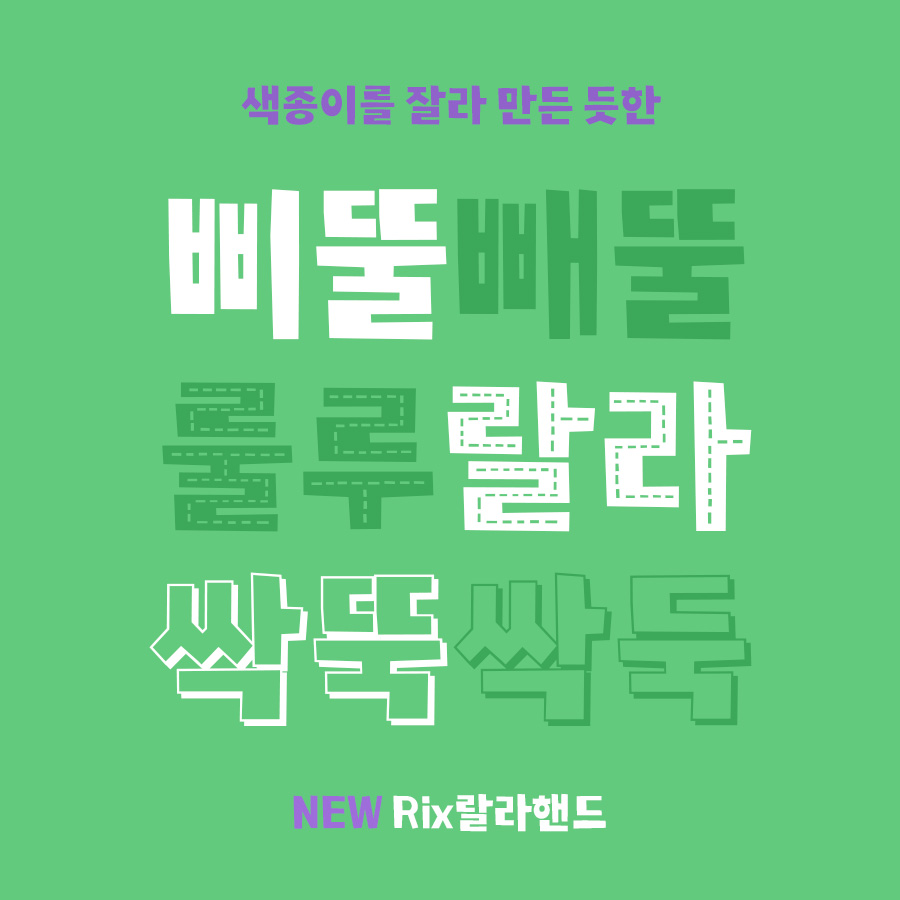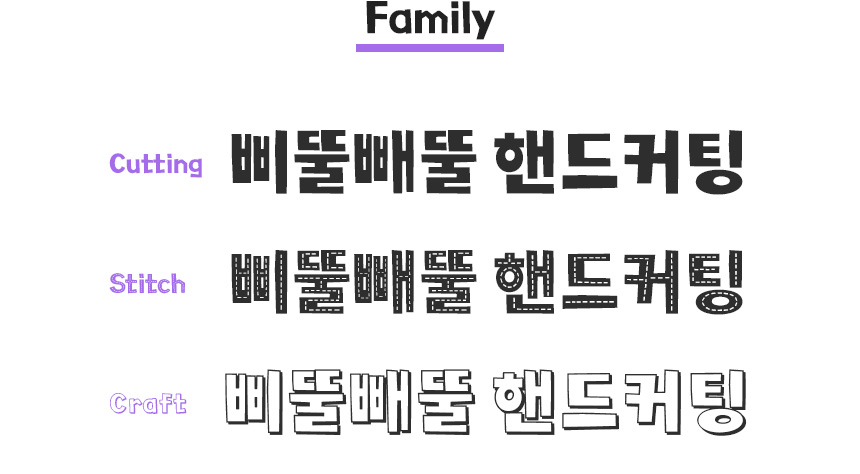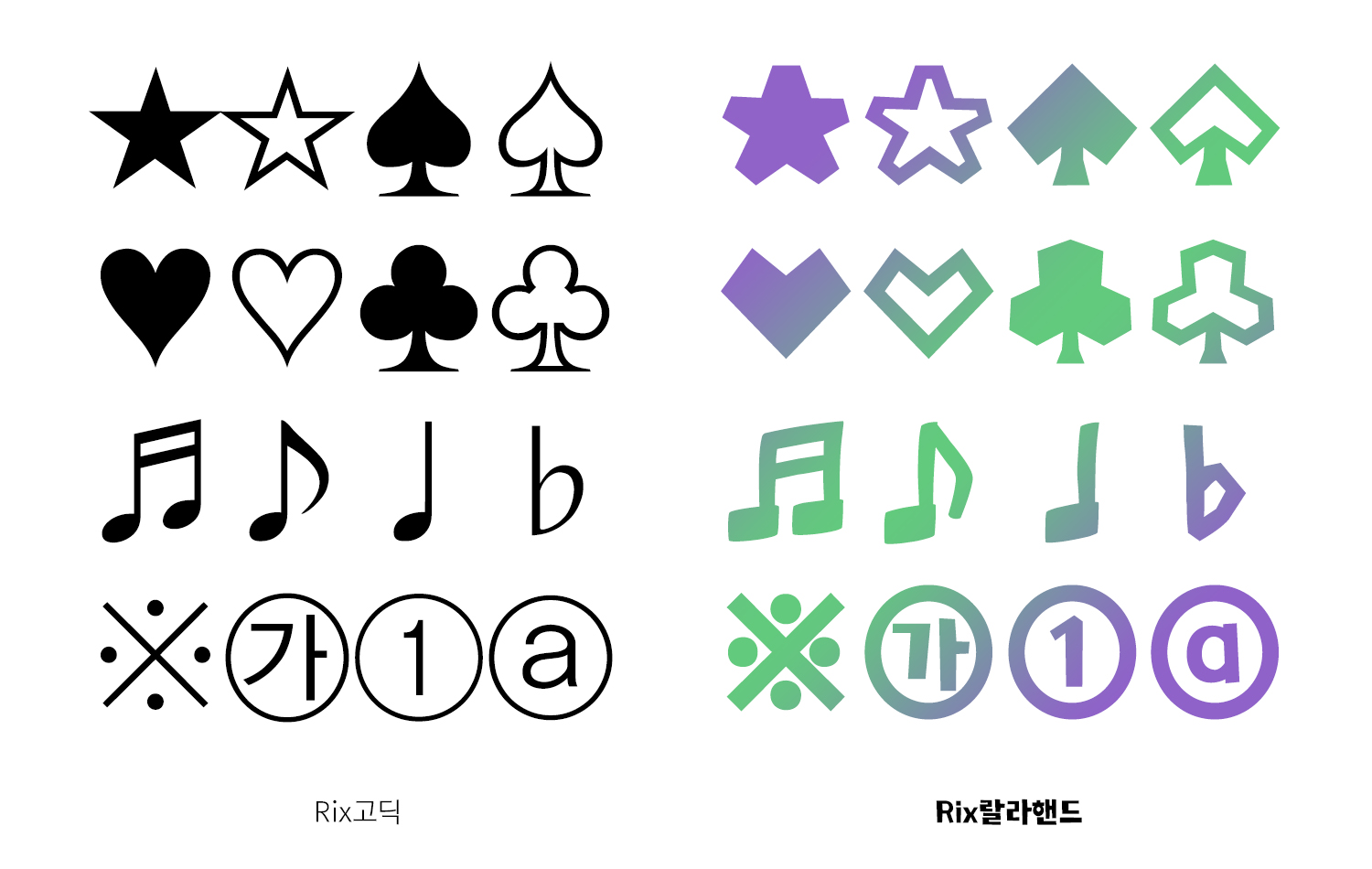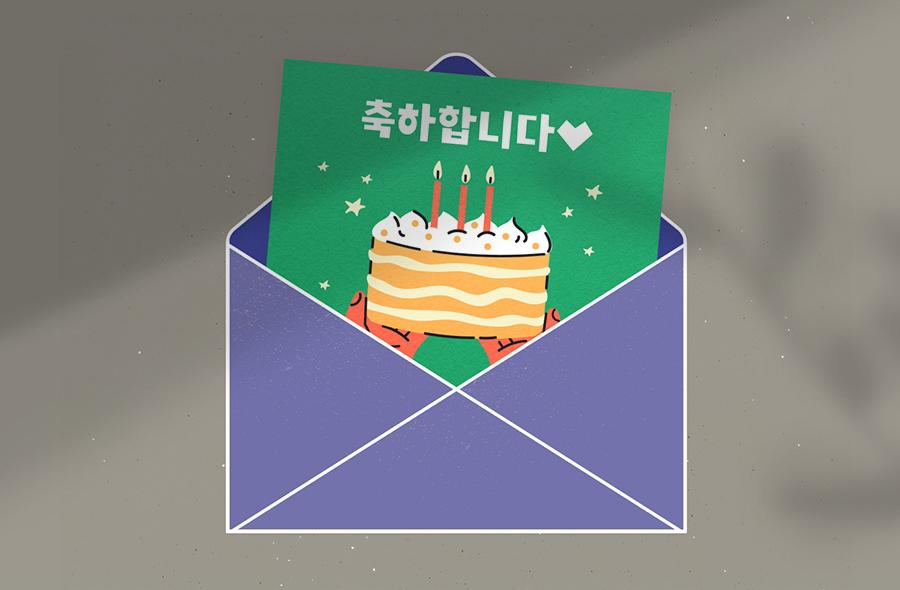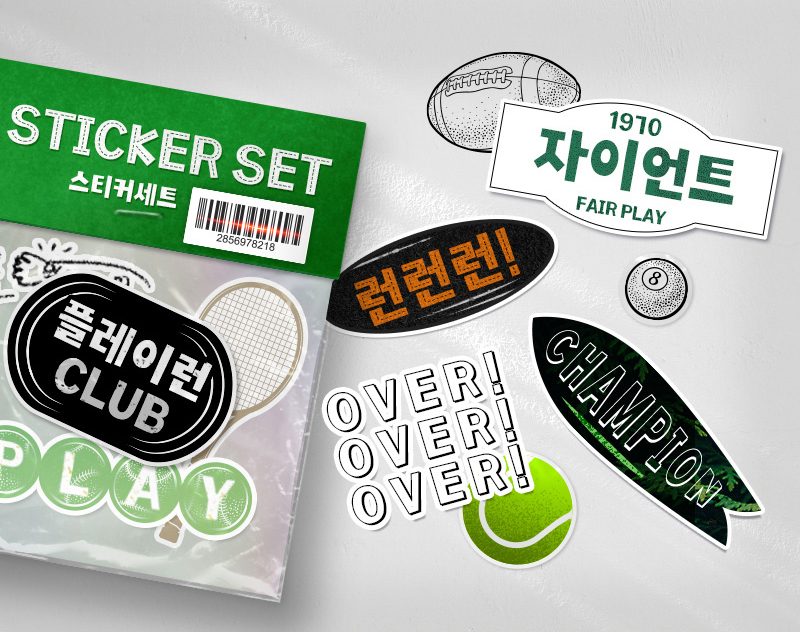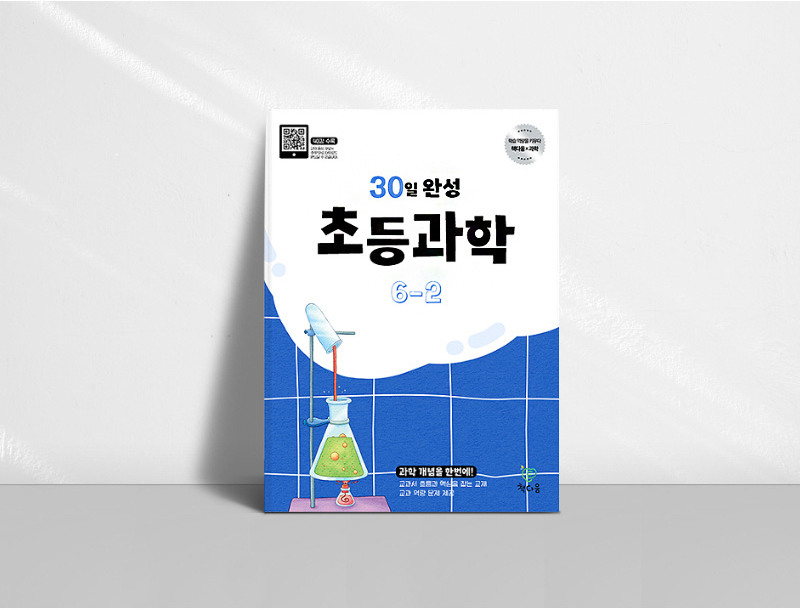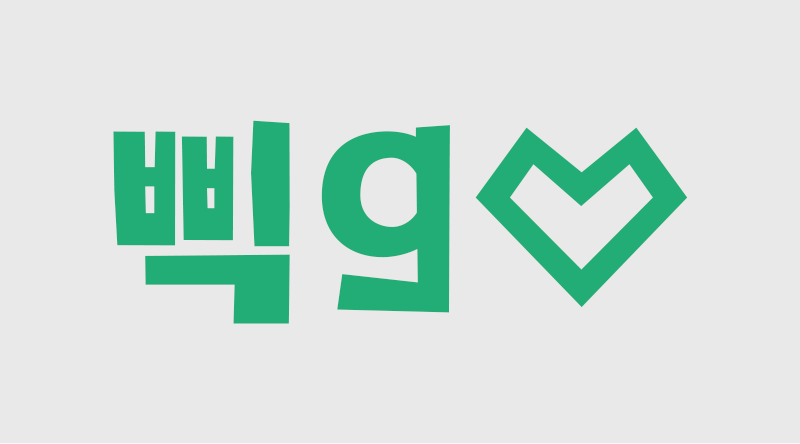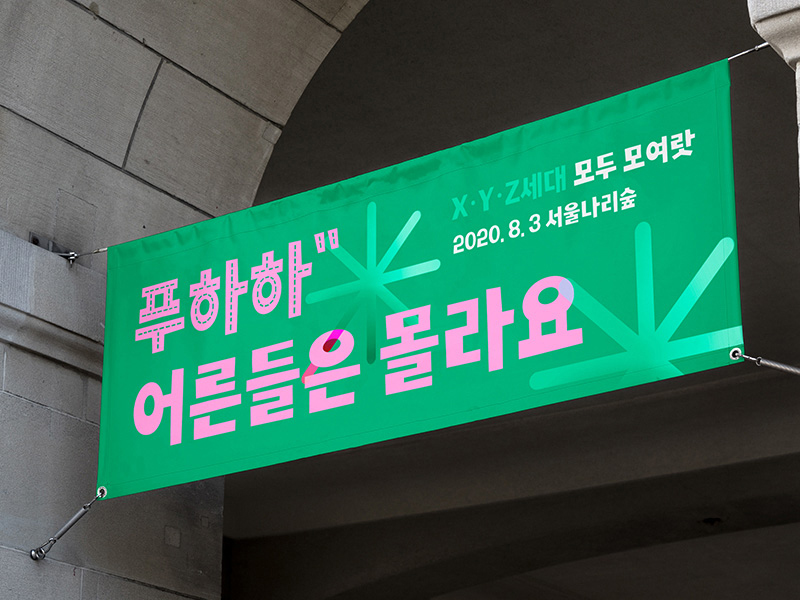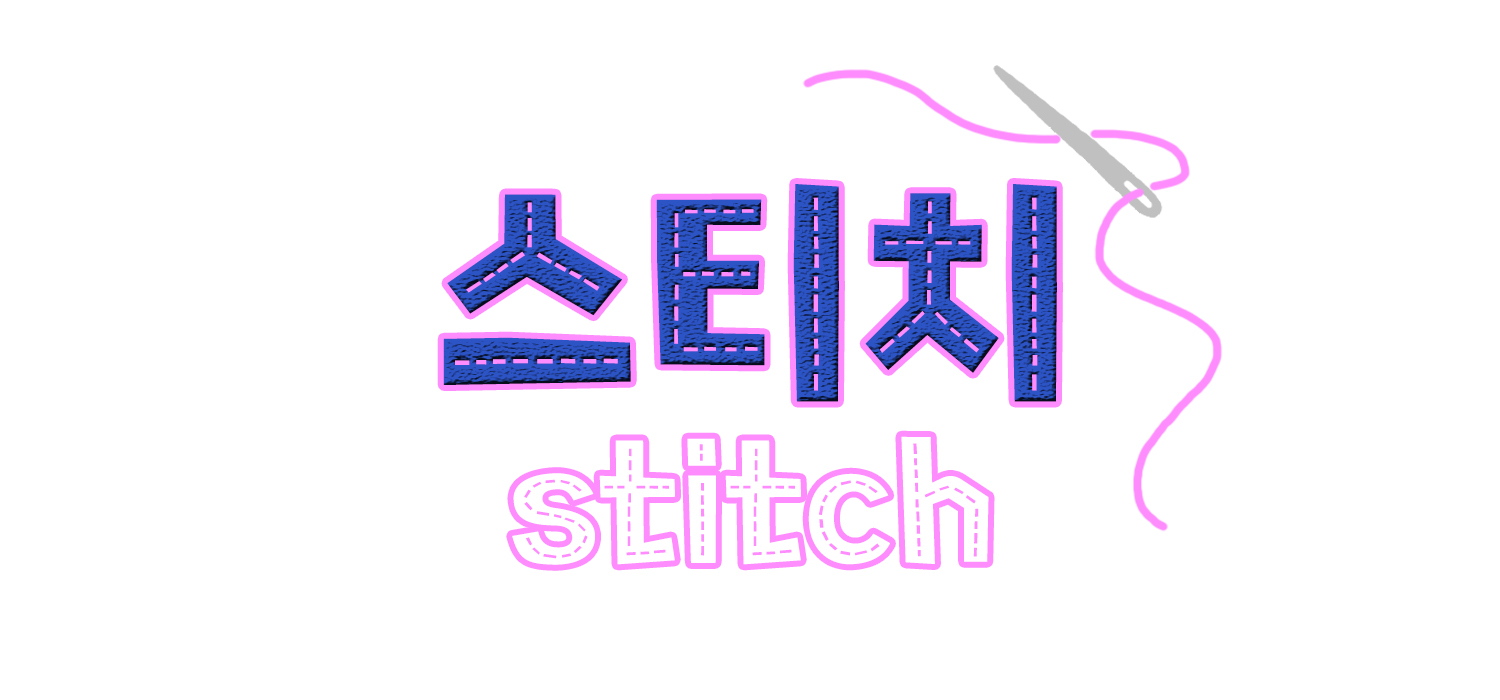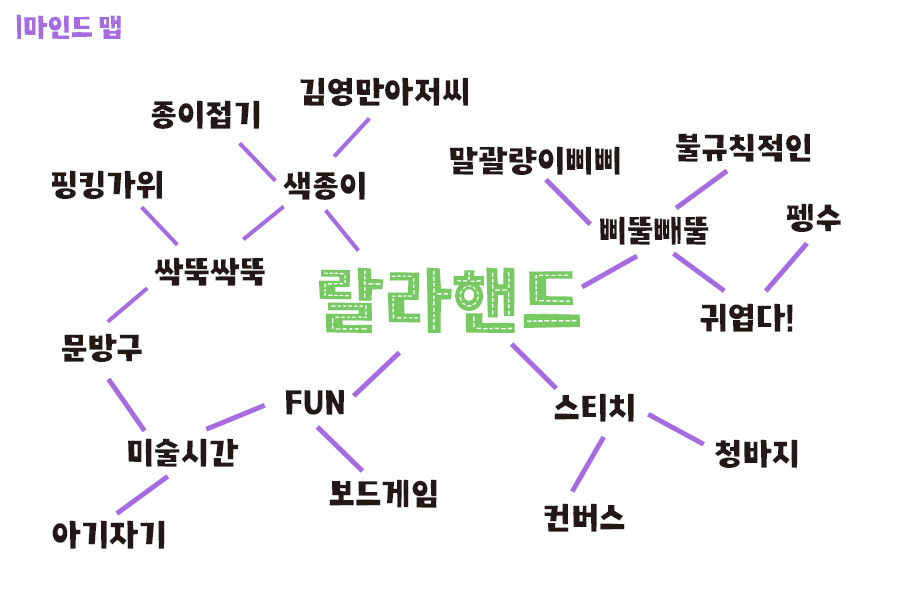
색종이를 잘라 삐뚤빼뚤, Rix랄라핸드
릭스폰트의 8월 신서체를 소개합니다. 보자마자 사랑스러워버리는 「Rix랄라핸드」라는 이름을 갖게 된 친구예요.(이름마저 귀여운 너란 폰트ㅠ) 색종이를 삐뚤빼뚤 잘라 만든 자유분방함 그 자체. 자세히 보면 볼수록 매력에 빠져드는 폰트! 먼저 폰트를 디자인해주신 김수정 디자이너와 인터뷰한 내용 함께 보실까요?
폰트를 알려면 디자이너를 알아야지_폰트 디자이너 인터뷰
폰트를 딱 보자마자 '귀엽다!'라는 생각을 했는데요. 어떻게 기획하게 되신 서체인가요?
회사에서 매달 아이디어 회의를 진행하고 있었는데, 회사에 필요한 서체가 무엇일까 고민을 하였고 다양한 자료를 조사하였습니다. 그러던 중 '핸드컷팅'이라는 소재를 글자에 적용하면 재미있겠다 생각이 들어 제작하게 되었습니다.
제작자피셜! 'Rix랄라핸드' 폰트의 가장 매력적인 부분은?
'Rix랄라핸드'는 Cutting, Stitch, Craft 3종으로 이루어진 폰트입니다. Cutting을 기본형으로, 다이어리 꾸밀 때 한 번쯤 해 보았던 드로잉(낙서) 참고하여 Stitch, Craft 효과를 만들었습니다. 형태적으로 삐뚤빼뚤, 자소 비대칭 형태가 매력적이라고 생각합니다. 효과가 들어간 Stitch, Craft 같은 경우에는 18pt이상으로 사용했을 때 디테일이 살아 더 예쁘게 사용 가능합니다. 효과와 효과를 오버랩하여 그래픽적으로 다양하게 사용할 수 있는 점이 매력포인트 같습니다.
본격 Rix랄라핸드 파헤치기.
폰트가 탄생하기까지는 7월 신서체 소개 포스팅에서도 언급했듯 정말 많은 시간과 과정들이 필요합니다. 「Rix랄라핸드」역시 수 개월의 디자인 작업 후에 여러 아이디어와 생각들이 모여 이름이 완성되고, 출시하는 단계까지 오게 되었는데요! 까도 까도 계속 나오는 양파 같은 매력의 이 폰트, 중요한 부분 중 하나인 폰트명이 만들어진 과정부터 함께 보시겠습니다*´∀`*
「랄라 핸드」라는 폰트명이 다소 생소할 수 있는데요, 이 이름은 신나고 기쁠 때 노래하는 표현인 '룰루랄라'의 랄라와 손으로 잘라서 만든 것을 뜻하는 '핸드컷팅(Hand Cutting)'의 핸드를 합쳐 만든 말입니다. 마인드 맵에서 보이듯 다양하고 재미있는 표현과 단어들이 떠올랐던 아이에요.
팀원들 대부분 이 글씨를 봤을 때 뭔가 자유분방하고 즐거운 느낌을 받았고, 아이들이 색종이를 잘라 만든 듯한 형태로 느껴져 폰트명으로 '랄라핸드'가 최종 선정되었답니다. 글씨를 써 보면 더 확실히 느낄 수 있을 거예요. 기대하시라!
매력 포인트 하나. 특수문자도 랄라핸드화
어떤 부분이 다른지 확실히 비교해드리고자 베이직한 본문형 서체로 잘 알려진 'Rix고딕'과 비교해 보았는데요. 가위로 잘라 만든 글씨처럼 특수문자에도 적용된 랄라핸드 스타일. 특히 음표들 표현된 게 참 귀엽고 사랑스럽더라고요ღ'ᴗ'ღ
*Cutting/ Stitch/ Craft 3가지 패밀리 중 어느 것을 적용해도 특수문자는 아래와 같이 국문과 동일한 스타일로 적용됩니다.
매력 포인트 둘. 개성 넘치는 패밀리
위에 잠깐 언급했던 대로 「Rix랄라 핸드」의 패밀리는 총 3가지가 있습니다. Cutting/ Stitch/ Craft 이렇게 3종으로 이루어진 폰트인데 기본 스타일의 Cutting부터 효과를 넣은 Stitch, Craft 모두 각각의 개성이 다르고 쓰임새도 달라서 쓰는 재미가 있어요. Cutting은 폰트 자체의 특징인 들쑥날쑥한 두께와 자유분방함을 잘 보여주고, Craft는 좀 더 가볍고 애니메이션 같은 느낌을 주죠. 그리고 Stitch의 매력은 밑에 계속.. 개인취향에 의해 좀 더 딥하게 파헤쳐봅니다.
매력 포인트 셋. 스티치 : 자기주장이 강한 편
3종의 스타일이 있는데 그중에서 가장 독특한 것을 꼽으라면 아무래도 스티치(Stitch: 바늘땀, 바느질하다. 꿰매다) 같아요. 청바지에 있는 박음질 같기도 하고, 종이를 자를 때 미리 그려놓는 실선 같기도 해요. 글자의 가운데를 가로질러가는 이 스티치가 아주 매력 뽀인트랍니다. 이 폰트 스타일은 잘라 만든 느낌을 살리기 위해 추가된 타입으로 어디에서도 본 적 없는! 그런 새롭고 신선한 느낌을 줍니다.
글자에 Stroke(획) 효과로 테두리선 색를 넣으면 안에 스티치 선 색도 바뀌는 매직!
이 폰트의 매력은 여기서 끝이 아니죠~
이제 「Rix랄라핸드」의 컨셉에 대해 좀 더 자세히 알아볼게요.
먼저 '랄라핸드'라는 이름을 갖게 된 이유, 삐뚤빼뚤 색종이를 잘라 만든 느낌을 살리기 위해 자소(낱글자)를 비대칭으로 디자인했다는 점! 위에 보시다시피 'ㅂ'은 양쪽이 대칭적인 구조를 가진 자소인데 랄라핸드는 왼쪽과 오른쪽 굵기가 다르도록 비대칭적으로 디자인되었죠.
또한 글줄에서 느껴지는 율동감을 살려 글자의 넓이를 변칙적으로 각각 다르게 설정했습니다. 덕분에 더 자유분방하고 재미가 더해진 느낌!
뾰족한 꺾임과 사선 마무리로 삐뚤빼뚤하게 표현된 디테일.
적당히 두꺼운 굵기를 갖고 있어, 어떤 이미지나 영상의 타이틀로도 위트 있게 연출할 수 있습니다.
| Rix랄라핸드 적용 이미지 샘플
플래카드, 스티커, 교재, 패키지 등 안 어울리는 곳이 없는 폰트.
디자인적으로 눈을 사로잡는 주목성도 있으면서 또 개성은 개성대로 다 가진 폰트라고 해도 과언이 아닌데요! 특히 어린이와 관련된, 귀엽고 심플한 스타일의 일러스트나 디자인과 잘 어우러집니다.
축하 카드에도 너무 귀여워!